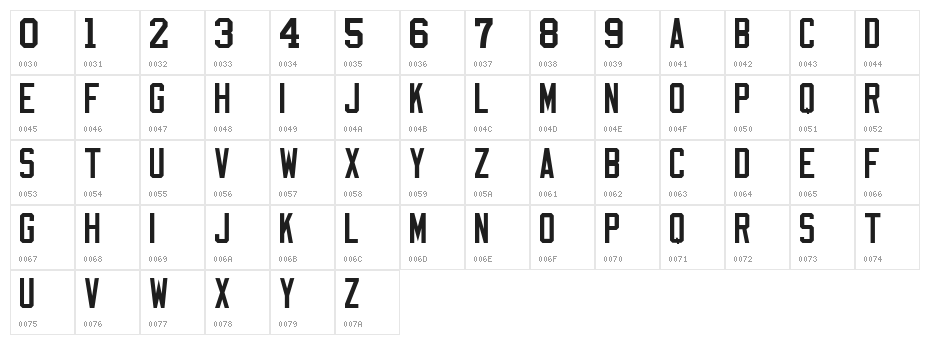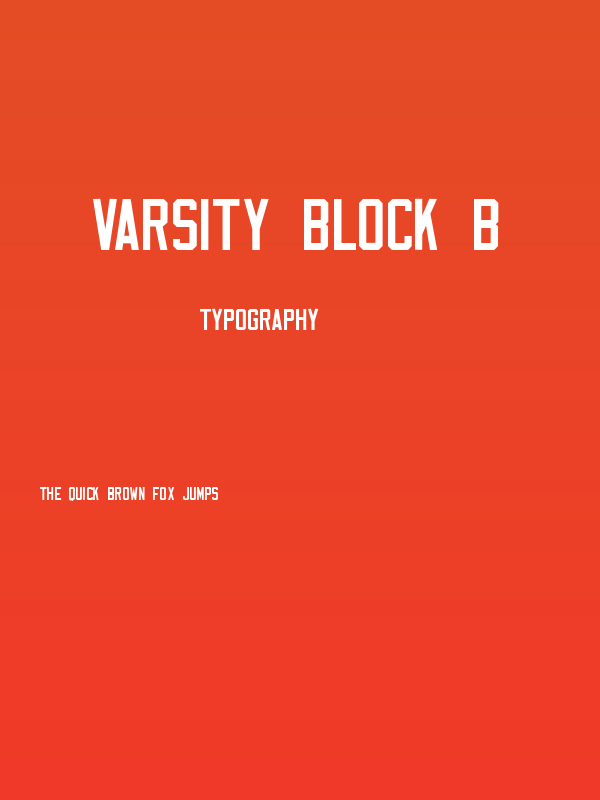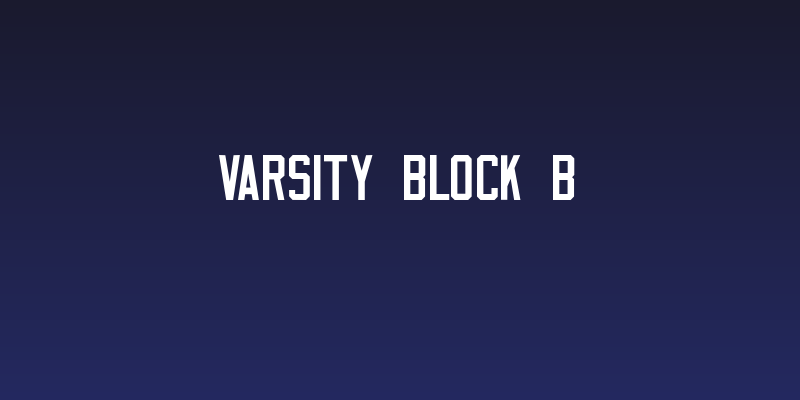
Varsity Block B Font
| Vorgeschlagene Projekte | Ideal for sports team branding, event posters, merchandise, and any project needing a bold, impactful typeface. |